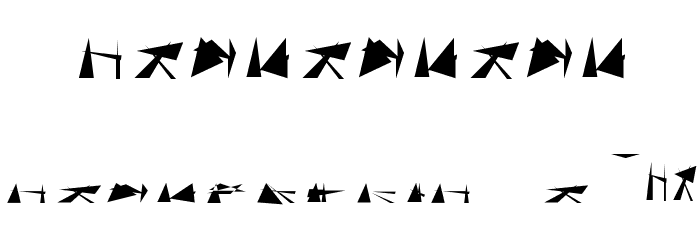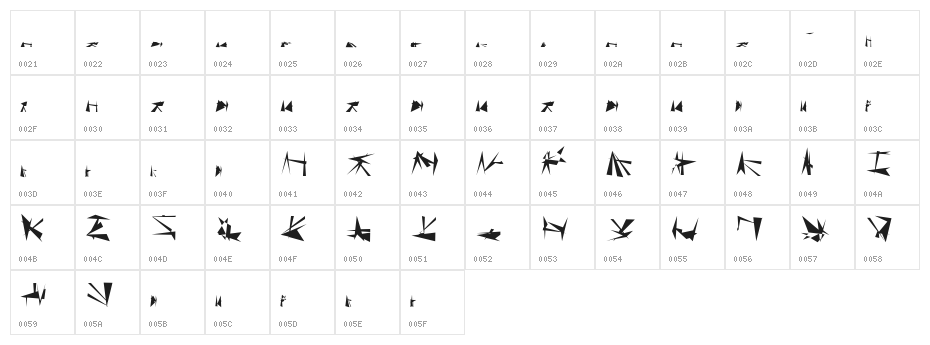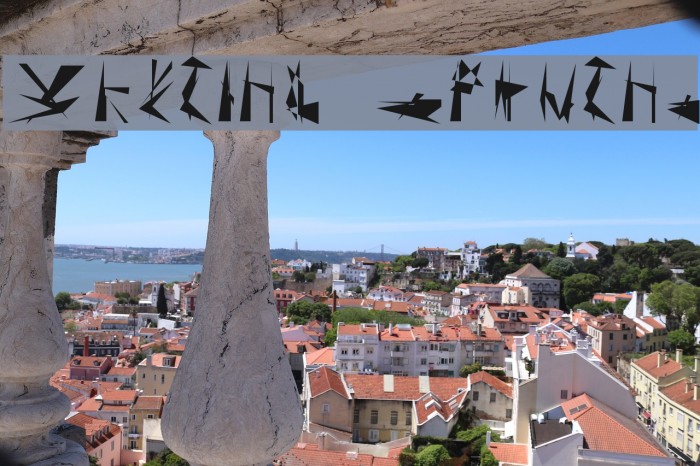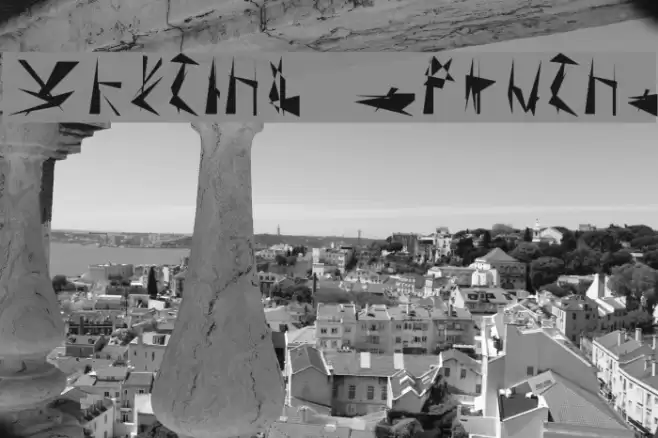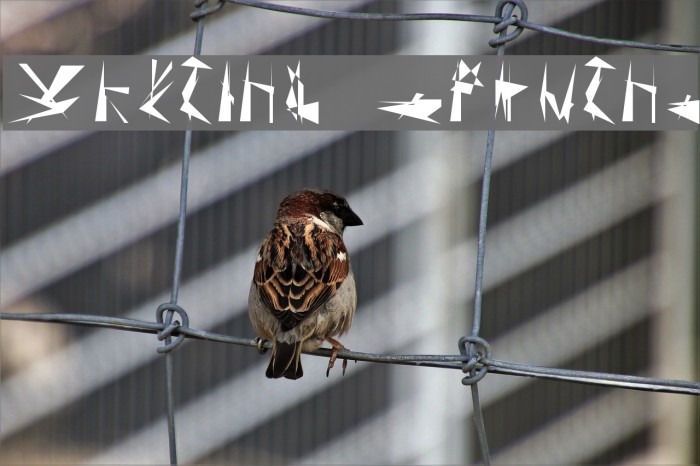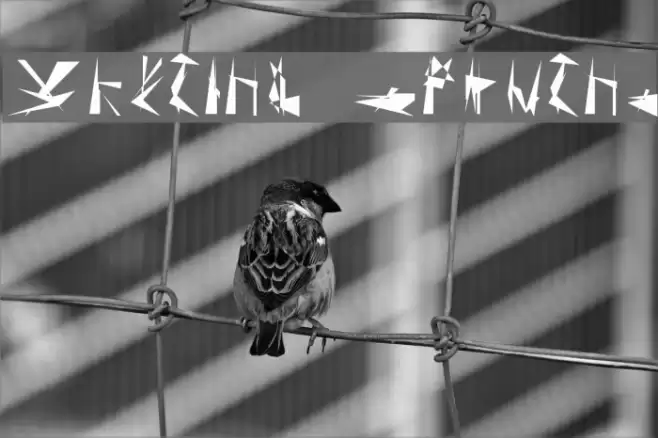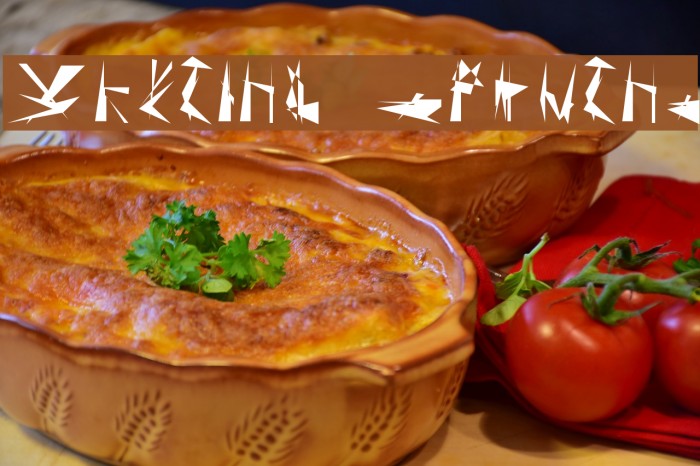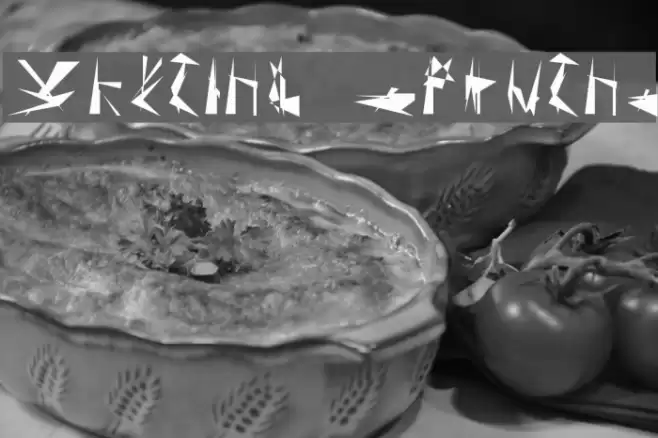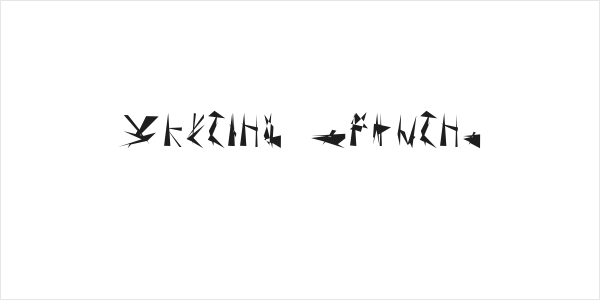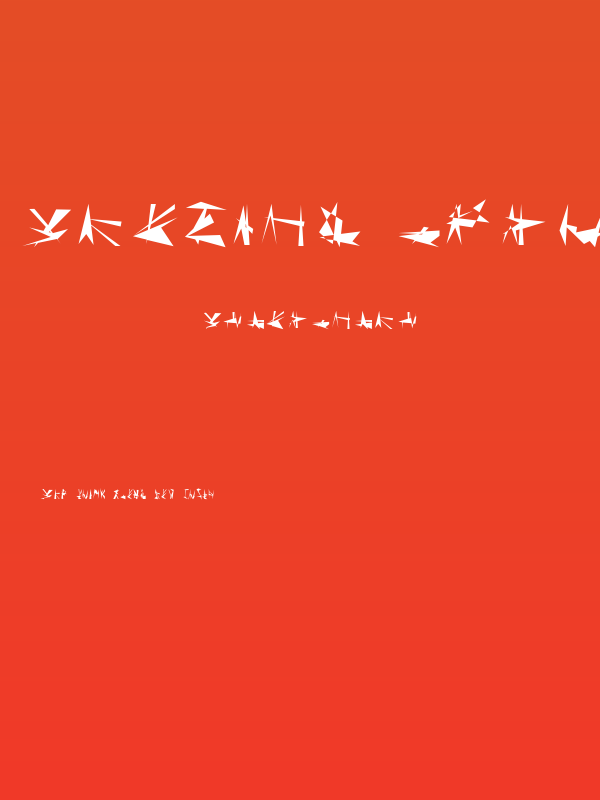
Tholian Regular Font
| Stile generale | Futuristic, Artistic |
| Caso d'uso | Logos, Posters, Artistic Displays |
| Progetti proposti | Ideal for sci-fi themed posters, album covers, video game graphics, and experimental art projects. |